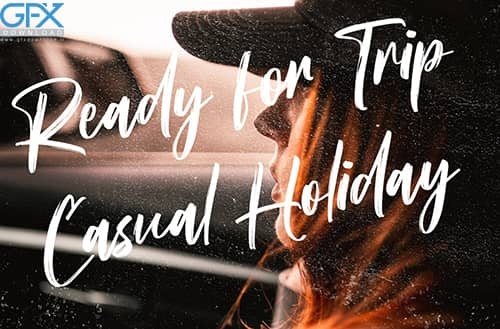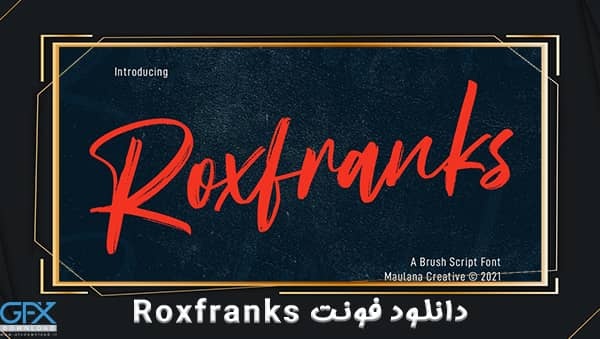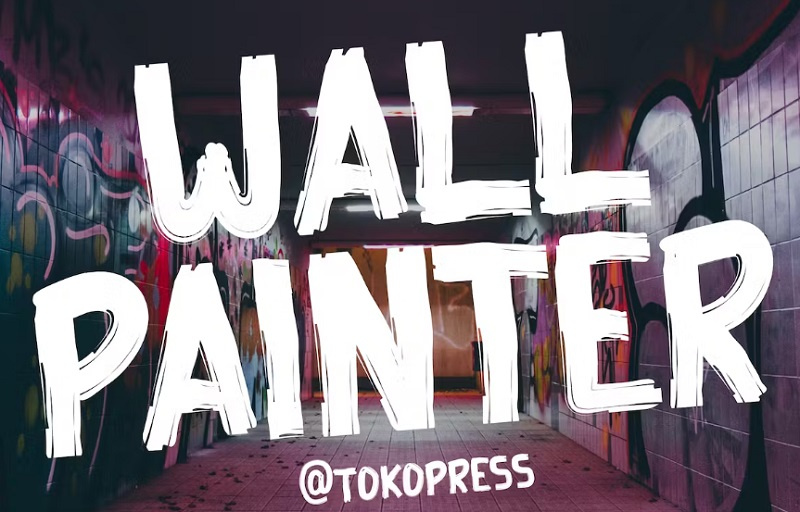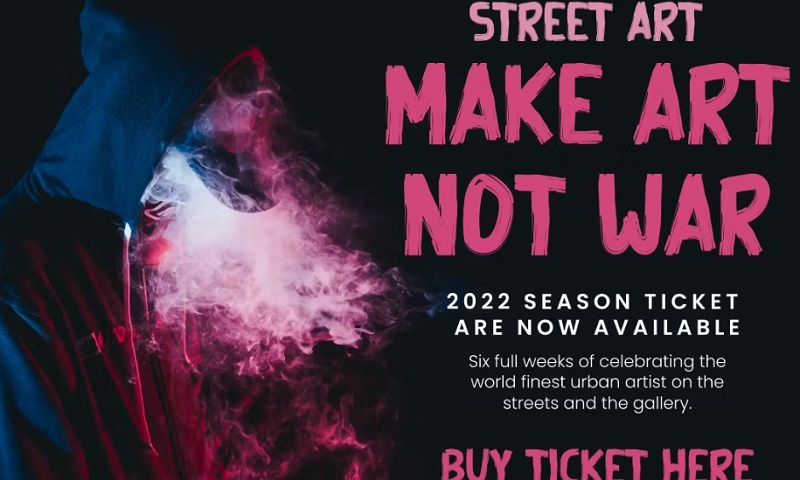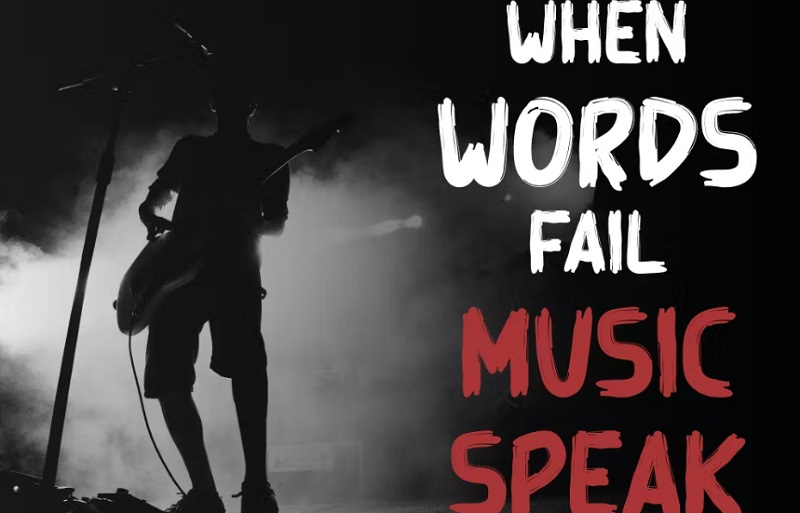
Roxfranks یک فونت Fancy Brush Script است. با قلم موی خشن ، کاراکتر های کج و سرگرم کننده با کمی چسبندگی. دانلود فونت انگلیسی خشن Roxfranks برای ارائه کارهای خلاقانه مناسب است. فونت Roxfranks بیش از 100+ زبان را از چند زبانه پشتیبانی می کند. این فونت برای طراحی لوگو ، رسانه های اجتماعی ، عنوان فیلم ، عنوان کتاب ، یک متن کوتاه حتی یک متن طولانی و برای فونت متن ثانویه با sans یا serif مناسب است. با فونت انگلیسی Roxfranks یک کار خیره کننده انجام دهید.
2- دانلود فونت انگلیسی خشن Wall Painter
این فونت انگلیسی خشن با نام Wall Painter می باشد که با طراحی سخت و خشن مناسب برای عناوین ورزشی، پوستر، عنوان فیلم، پوستر موسیقی، کاور یوتیوب، کاور رسانه های اجتماعی و غیره... می باشد. این فونت شامل فایل های OTF/TTF/WOFF است.
3- دانلود فونت های خشن انگلیسی
یک فونت خشن به سبک دست خط است که بیش از 100 زبان را پشتیبانی می کند. این فونت خشن انگلیسی برای طراحی لوگو، عنوان فیلم، عنوان کتاب و هر پروژه گرافیکی دیگر مناسب است. شامل فرمت های OTF و TTF می باشد.
4- فونت انگلیسی خشن و زمخت
Breaking Mad یک فونت انگلیسی مناسب برای پوسترهای فیلمهای اکشن یا ترسناک، طراحی لوگو، تیزرهای تبلیغاتی ورزشی و ... می باشد. این سبک فونت خشن برای ایجاد جلوهای قدرتمند، جسورانه یا صنعتی استفاده میشوند.